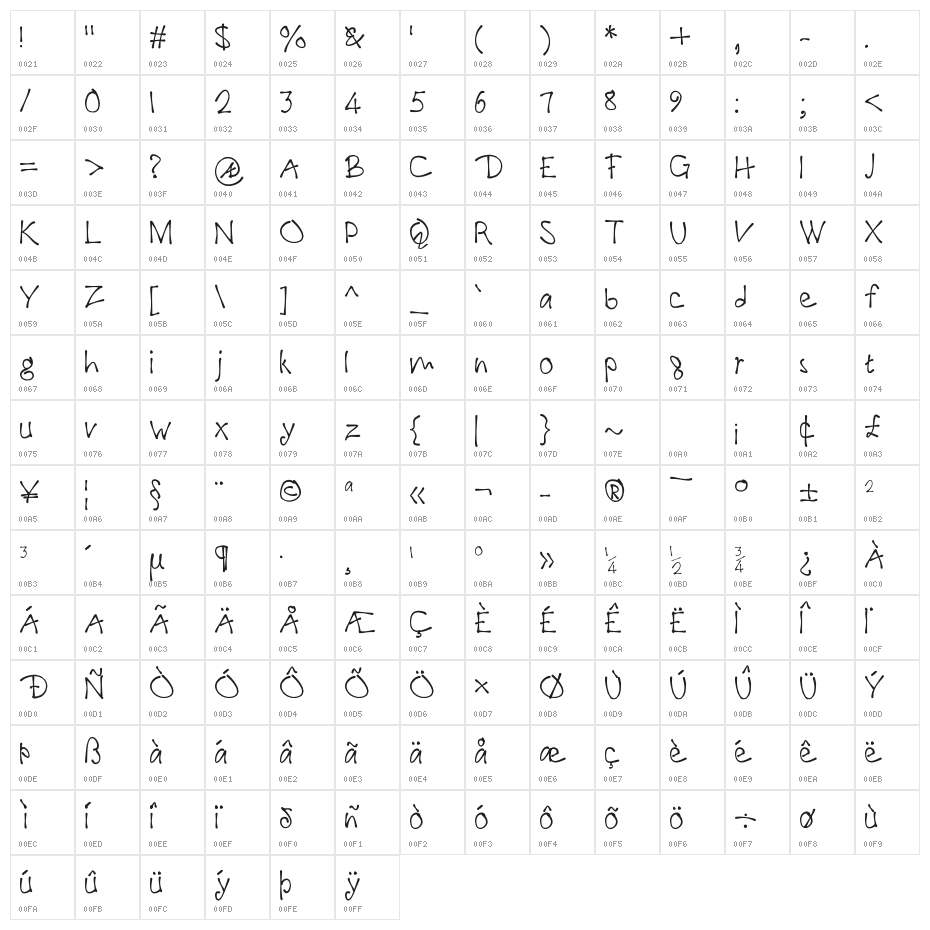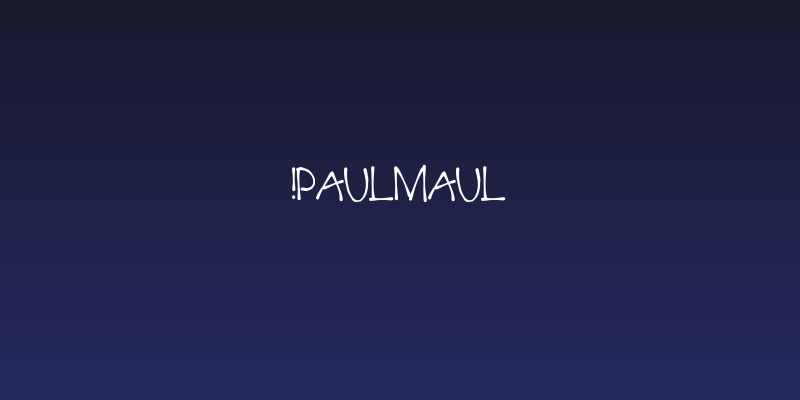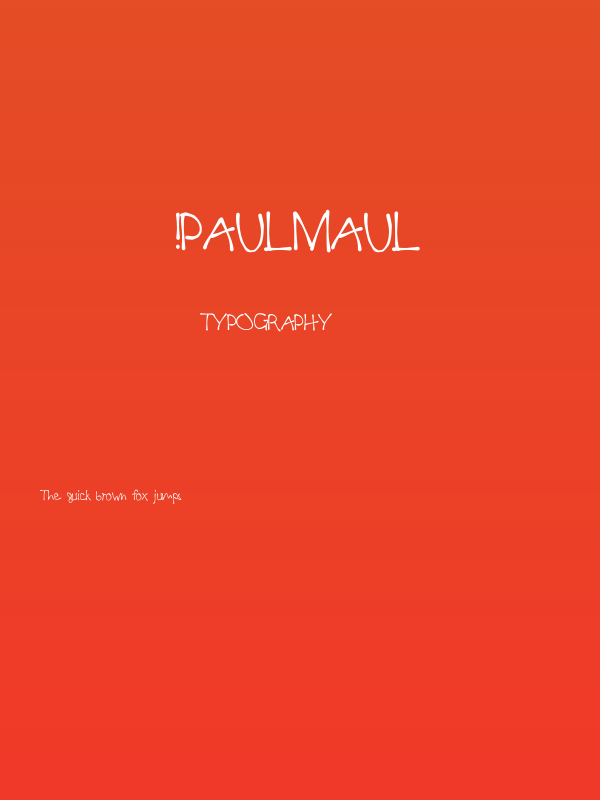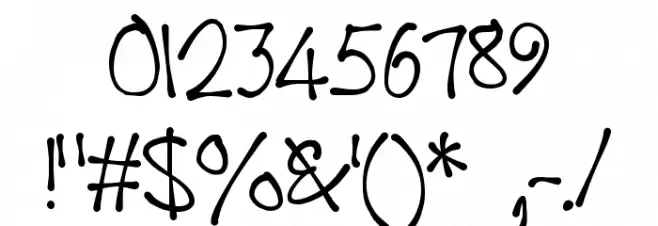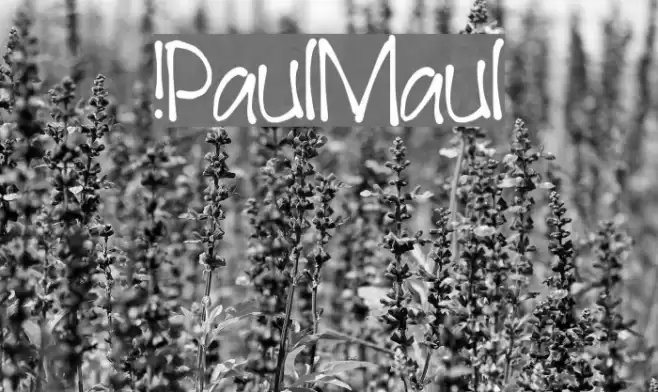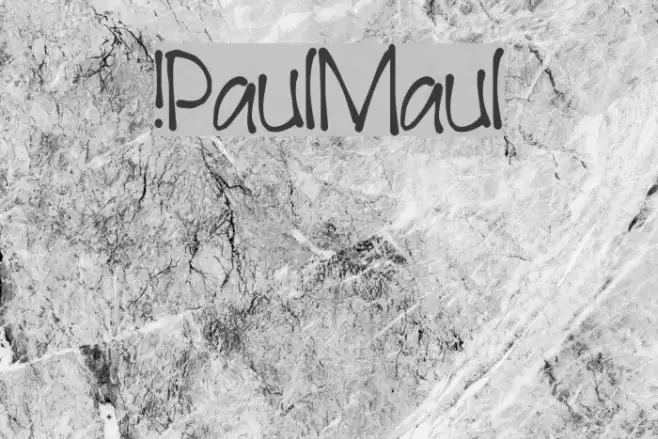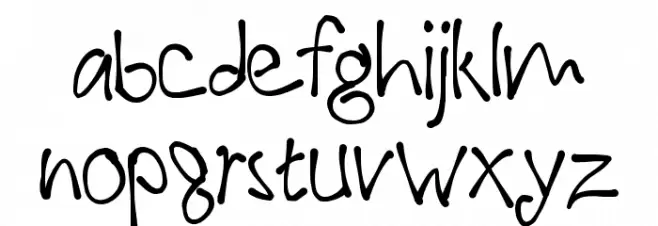
!PaulMaul Font
| Stile generale | Casual, Playful |
| Caso d'uso | Logos, Headlines, Creative projects |
| Progetti proposti | Ideal for greeting cards, children's books, creative posters, and personal branding. |